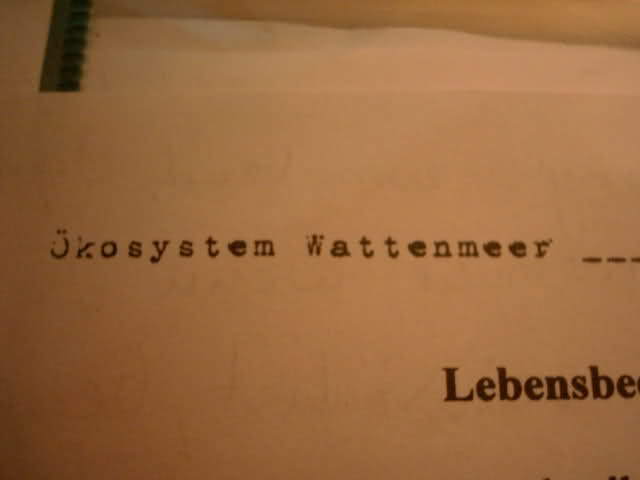
Schriftart mal wieder gesucht ;)
ich suche den Namen (und Download) einer Schriftart, die meine Lehrerin immer benutzt... . Ich bräuchte sie für ein Referat.
Weiß jemand, welche das ist (mit Ökosystem...)?
Das sieht stark nach einer Schreibmaschine aus, genau diese wird es digital also mit hoher Wahrscheinlichkeit nicht geben. Ich gehe mal davon aus, dass Du auch kein Geld ausgeben willst, also empfehle ich Dir auf einer der einschlägigen Freefonts-Seiten nach "Typewriter-Fonts" oder Ähnlichem zu suchen, vielleicht ist etwas dabei was dem nahekommt.
Also es ist mit Sicherheit mit dem PC geschrieben, danke dir trotzdem :huhu: .
also, es gibt einen typewriter-font, der „1942 report“ heißt – müsstest du mal googeln (oder bingen ...). einige zeichen sind schon sehr ähnlich.
der font ist aber extrem seltsam ... wie macht deine lehrerin das – benutzt die nie „ü“ oder das scharfe s? (ä und ö gibt's aber.)
Diese Schriftart benutzt sie glaub ich nur als Überschrift fürs Wattenmeer.
Bei Genetik wars ne andere... .
Aber die Schriftart sieht schon ziemlich gleich aus. Das ist sie bestimmt!
Aber woher weißt du das?
Scannt man das irgendwo ein?
>>> harting – das alte leiden mit den free fonts: wenn man sich an der – ähm, fundstelle – die „vollständige Buchstaben Mappe“ anzeigen lässt, ist dort, wo man gern ein ä, ein ö, ein ü und ein ß hätte, nur gähnende leere (da ist ja die 1942 report mit ä und ö schon zwei schritte weiter ...).
und, tja, wie man das macht? augen auf, sich erinnern, ein bisschen rumstöbern ... voilà. hat was damit zu tun, wie lange man sowas schon macht ... (und wie beim pilze suchen: ein bisschen glück ist auch immer dabei).
also wie schon geschrieben, müsste es 1942 Report sein. Ich habs mal ausgedruckt und verglichen. Sogar der Punkt oben beim r ist mit dabei.